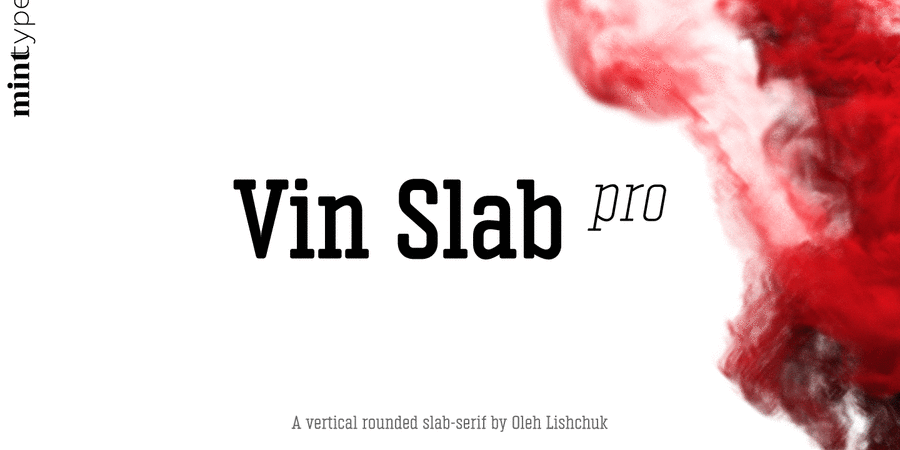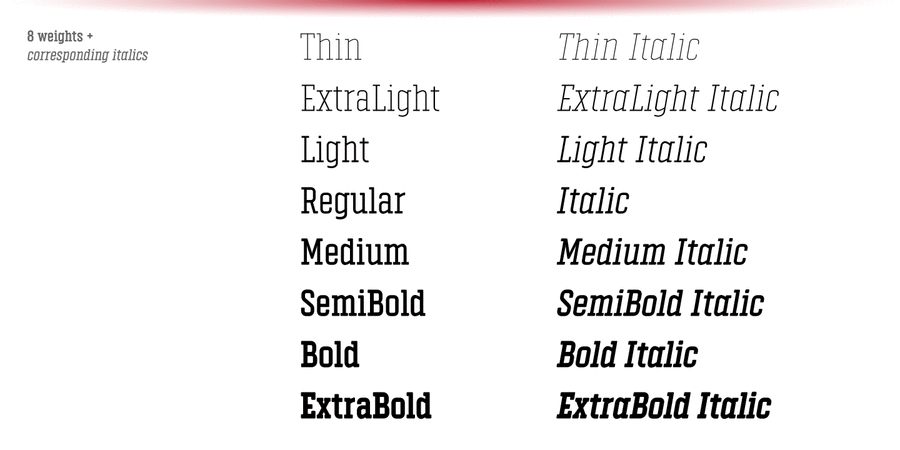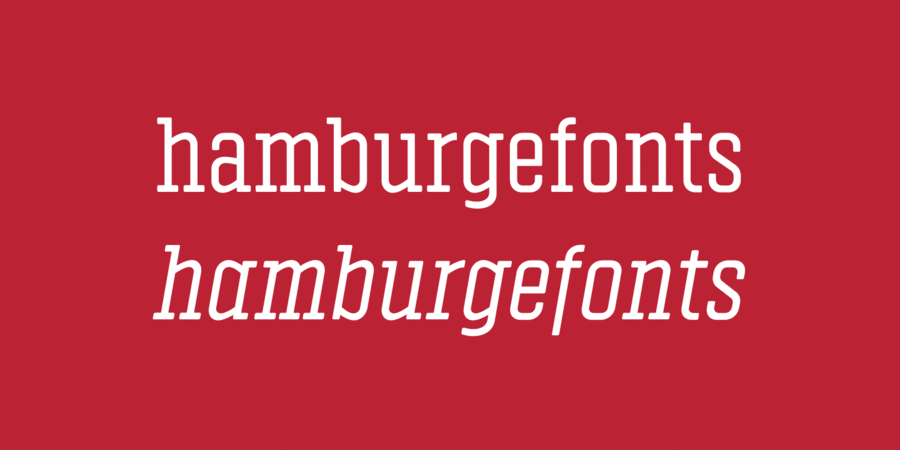
Опис гарнітури Vin Slab Pro – компактна жорстка брускова гарнітура зі збільшеним x-height та заокругленими кутами. Vin (він) – супергарнітура з трьох маскулінних шрифтових сімейств з яскраво вираженими вертикалями, прямокутними овалами та заокругленими кутами. Для більшої виразності всі три шрифти мають збільшену висоту рядкових. Шрифт розробив Олег Ліщук у студії Mint Type у 2018 році.
Особливості сімейства шрифтів Vin Slab ProХіт десятиліття:
Асоціації з сімейством шрифтів Vin Slab ProОсобистість і характер гарнітури:
неоновий, точний, рівний, прямокутний, тонкий, статичний, логічний, холодний, легкий, міський, інженерний, урбаністичний, креслярський, скляний, крихкий, прозорий, спокійний, дротяний, худий, стійкий, автоматичний, техногенний, твердий, чіткий, машинний, тісний, стиснений, стабільний, серйозний, практичний, прагматичний, технічний, якісний, міцний, надійний, впевнений, переконливий, авторитетний, брутальний, жорсткий, суворий, індустріальний, гучний, важливий, наполегливий, сильний, крутий, амбітний, важкий, сталевий, залізний, гарячий, монументальний
креслення, архітектура, інженер, Місто, електроніка, прилад, технології, конструктор, автоматика, урбаністика, дизайн, техніка, гра, авто, шутер, екшен, залізо, інструмент, промисловість, завод, Футбол, спорт, верстат, електростанція, енергетика, тренажери, ремонт, блокбастер, бойовик, нафта, селфі, паливо, кіно, поліція Гарнітура асоціюється з віком: